如何使用字体和字体大小来提高转化率
已发表: 2017-08-29字体是设计师在设计网站时经常忽略的最被低估的功能之一。 一个好的设计师知道排版的重要性以及它对观众的影响。 研究表明,您选择的排版具有增强或降低用户体验和观众情绪的能力。 如果访问者发现您的内容难以阅读或没有吸引力,他们可能会放弃该网站; 这反过来会降低您的转化率。 理想的字体选择可以改善用户体验,并且还能够反映您的业务愿景和目标。 目标不仅应该是创建一个具有高质量内容的网站,还应该创建一个具有视觉吸引力的高质量内容的网站。
如何选择完美的字体以及应该避免的错误:
选择合适的排版选择包括选择正确的字体类型、正确的字体大小、理想的颜色、行距和字距调整。 尽管与网站设计的其他方面相比,排版似乎无关紧要,但它在提高转化率方面起着关键作用。 在决定合适的排版时,应牢记一些注意事项。
- 为目标受众选择一种字体,以及一种代表您的品牌标识的字体
如果您对字体概念不熟悉,您可能认为 Calibri、Arial 等字体是为特定上下文设计的。 您需要开始跳出框框思考并继续根据目标受众和品牌标识选择字体。 每种字体都有自己的个性。 您的目标受众是千禧一代,还是试图接近更成熟的一代? 您的网站是针对特定性别开发的吗? 字体是否与您开展的业务类型相符? 这些是您在使用字体之前需要问自己的问题。
- 现代/当代字体
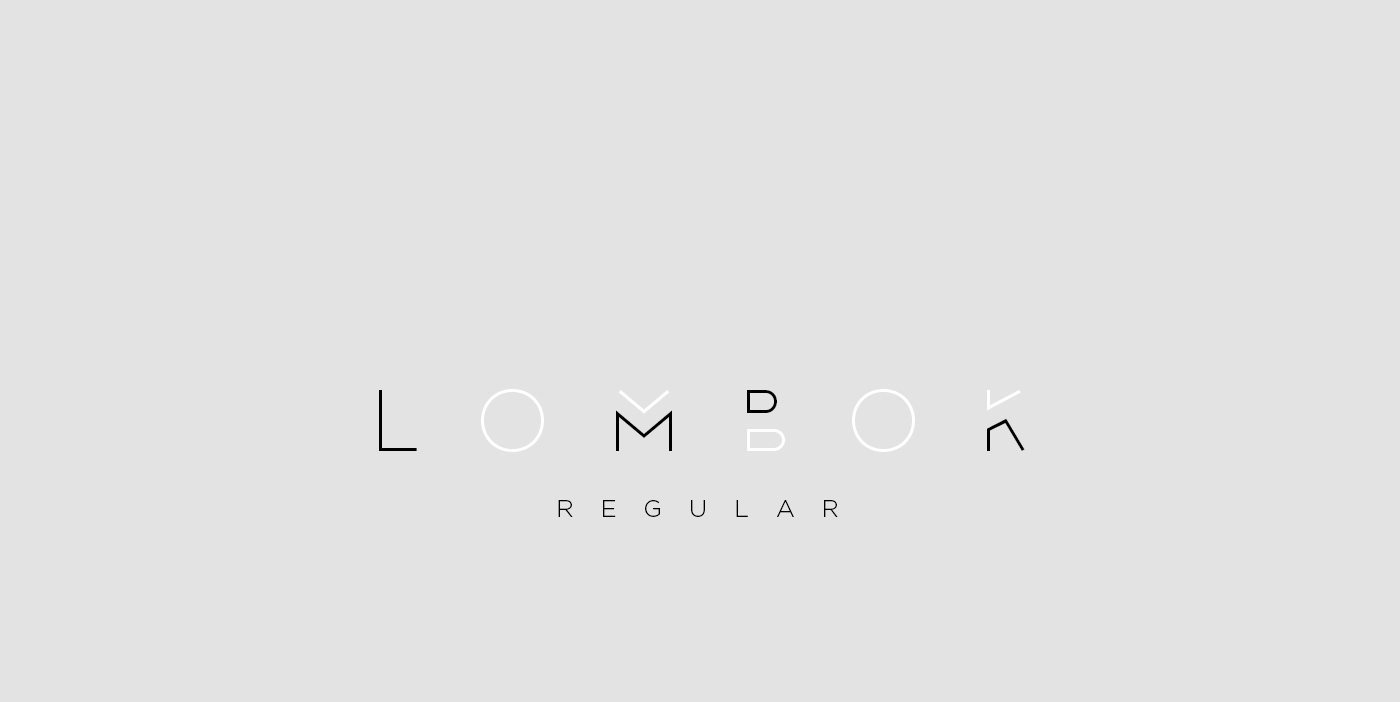
这些字体通常具有简约而整洁的设计。 他们的美丽在于他们的简单。 字符通常要么很瘦要么很粗,例如龙目岛。
- 繁体字
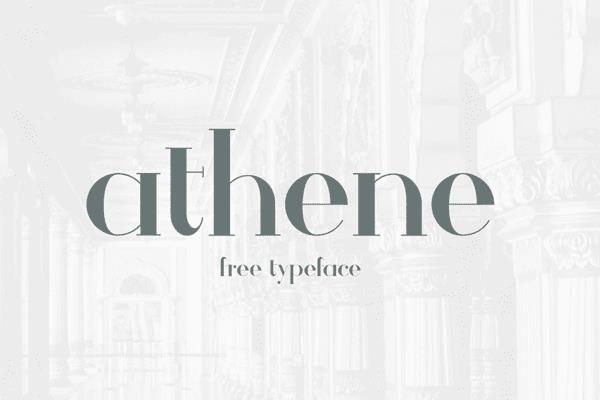
这些字体已经存在了很长一段时间,因此散发出一种更传统的氛围。 它们象征着舒适和可靠,以字体 Georgia、new times roman 等为代表。如果您希望您的网站具有老式和经典的个性,那么您应该选择这些字体。 Athene 和 Barbaro 等字体也可以达到目的。
- 精致与优雅
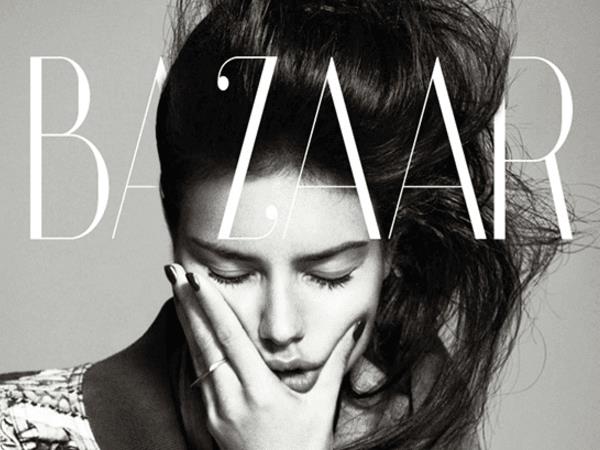
通常有很多拱形和曲线的字体通常用于美容或浪漫相关的网站。 例如,Castro 字体散发出浪漫的气息,而 Vanity 等字体非常适合创建与美容相关的网站。
- 粗体字体
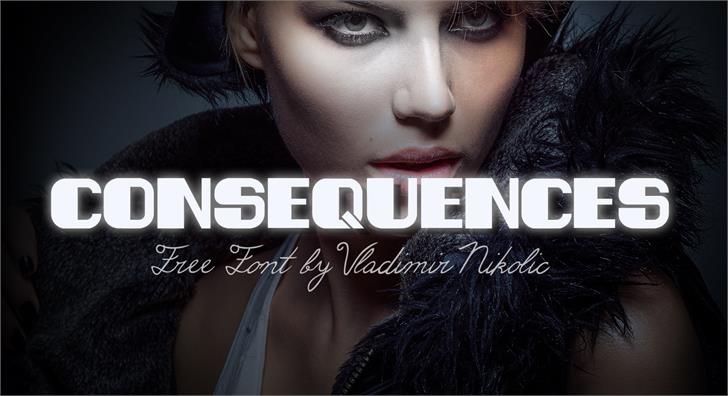
具有强烈和粗体字符的定义明确的字体通常用于做出粗体声明并立即抓住用户的眼睛。 一些很好的例子包括像 Consequences 和 Nevis 这样的字体。
- 个性化字体
您始终可以选择定制字体,专为真正捕捉您公司的精髓而创建。 它将帮助您创建自己独特的品牌标识。
- 可读性
您网站的目标应该是通过您的内容吸引客户,但如果您的内容不可读,这可能很难做到。 如果您网站的内容难以阅读,访问者更有可能离开您的页面。 这可能有助于提高跳出率和降低转化率。 下面列出了影响内容可读性的某些因素:
- 设计
虽然创意字体可以为您的网站增添活力,但绝对不能过度使用。 您不应该使字体过于奢侈以至于几乎无法破译。 有时少即是多; 因此,不要让访问者难以阅读内容,从而使事情变得过于复杂。 永远不要在可读性上妥协!
使用太多设计的字体会造成混乱,并散发出不整洁的外观。 尽量避免这个错误,因为它会给访问者造成混乱并导致整体负面印象。 创建网站时坚持使用一种或几种字体。
- 尺寸
像字体大小这样可能微不足道的东西仍然可以在准确地向网站访问者展示您的品牌愿景和身份方面发挥重要作用。 要实现的字体大小既不能太小,以免给观看者的眼睛带来压力,也不能太大而占据页面的大部分区域。 如果字体大小可读,您更有可能拥有更好的平台来与访问者互动。 此外,他们将更好地理解您的信息。 在当今时代,人们通过各种设备(智能手机、笔记本电脑、平板电脑等)访问互联网。 因此,您需要选择在不同界面之间兼容的字体大小。
- 行距和字距的重要性
行距和字距调整等因素有助于查看者感知内容的大致长度。 如果内容看起来太长或阅读起来太麻烦,访问者很可能会离开页面。 此外,如果字符或行之间的间距太宽或不够,用户可能会面临阅读文章的困难。 字距和行距需要等于每一行/字符; 否则,您的网站可能会有不专业的感觉。
- 配色方案
在选择配色方案时,您需要考虑目标受众及其偏好。 考虑目标年龄组、性别和利基市场; 然后相应地选择您的配色方案。 研究表明,女性通常更喜欢浅色,而男性则更喜欢更亮和更暗的颜色。 根据这些(和其他类似)因素,为您的字体选择合适的颜色。 您需要为您的品牌徽标选择一种主色,并为网站选择其他一些与您的主色相得益彰的颜色。
添加颜色可以真正使您的网站更加明亮,但是您绝不能添加太多颜色,以免它变成难以区分的明亮色调混乱。 颜色应该相互协调,而不是造成混乱。 这是空白步骤可以再次证明有利的地方。 白色间距是一个至关重要的方面,但通常没有得到应有的重视。 如果做得正确,它可以提高整体可读性并为您的网站增加技巧。
结论
专注于字体、大小和颜色等微小细节似乎是浪费时间和资源,但肯定会通过提高转化率来获得回报。 每种字体都有自己的个性,每种颜色都讲述着不同的故事。 他们一起有能力影响观众的情绪和情感。 因此,这是一种将随机访问者转换为潜在客户的简单方法。